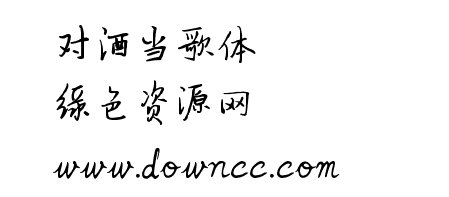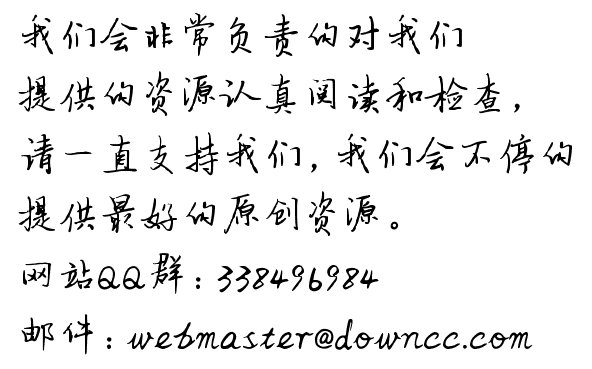
對酒當歌體給人一種快意江湖的俠義之感,字跡深沉有力,運筆細膩不失流暢,格局端方而嚴謹,給人印象審核,來綠色資源網即可體驗哦!
“對酒當歌,人生幾何?譬如朝露,去日苦多??斠钥?,憂思難忘。何以解憂?惟有杜康?!薄獙飘敻梵w。
本字庫是在國家標準簡體字庫GB2312所包含6763漢字的基礎上,又增加了近200常用字,已經覆蓋了大陸99.75%的漢字使用頻率,足以滿足日常需求。
對酒當歌體,給人一種歷經千帆回首往事的落拓不羈感受,更是醉意紅塵的瀟灑氣概,同時字體清晰明亮,有著不錯的感官體驗,運用在閱讀上比較出色。